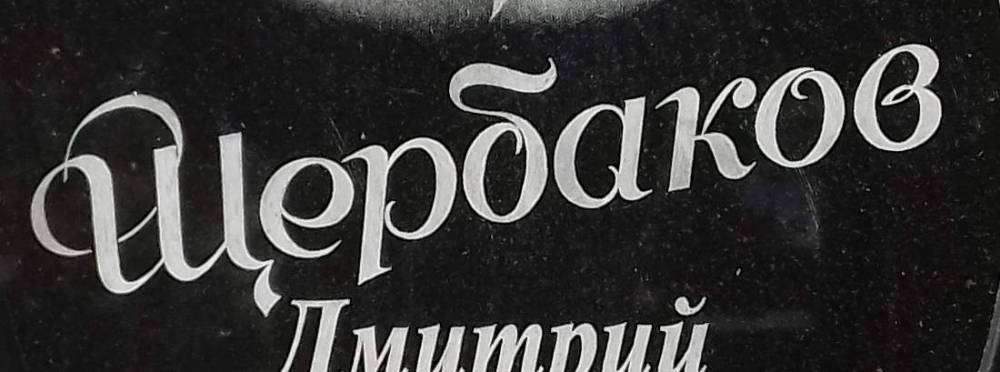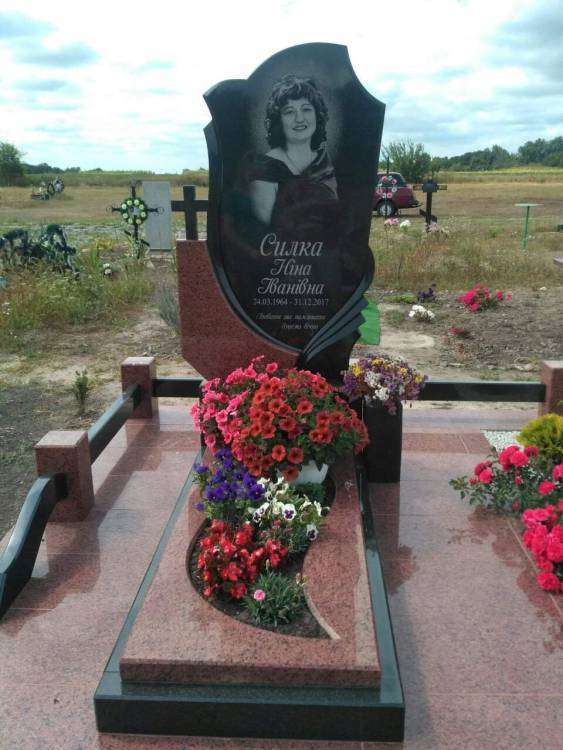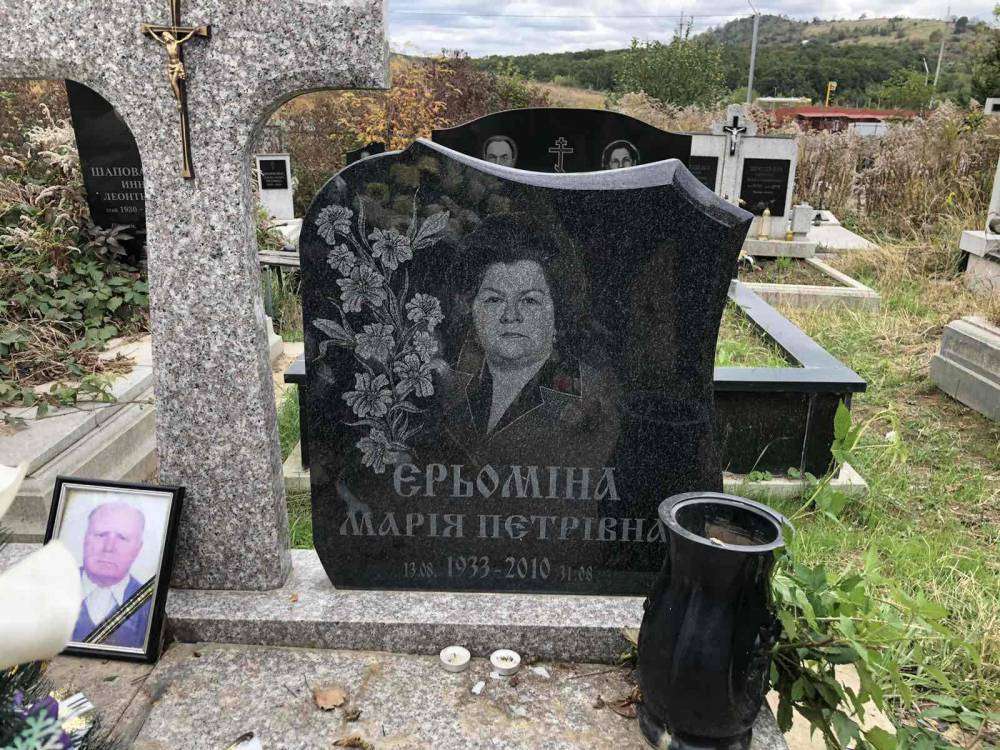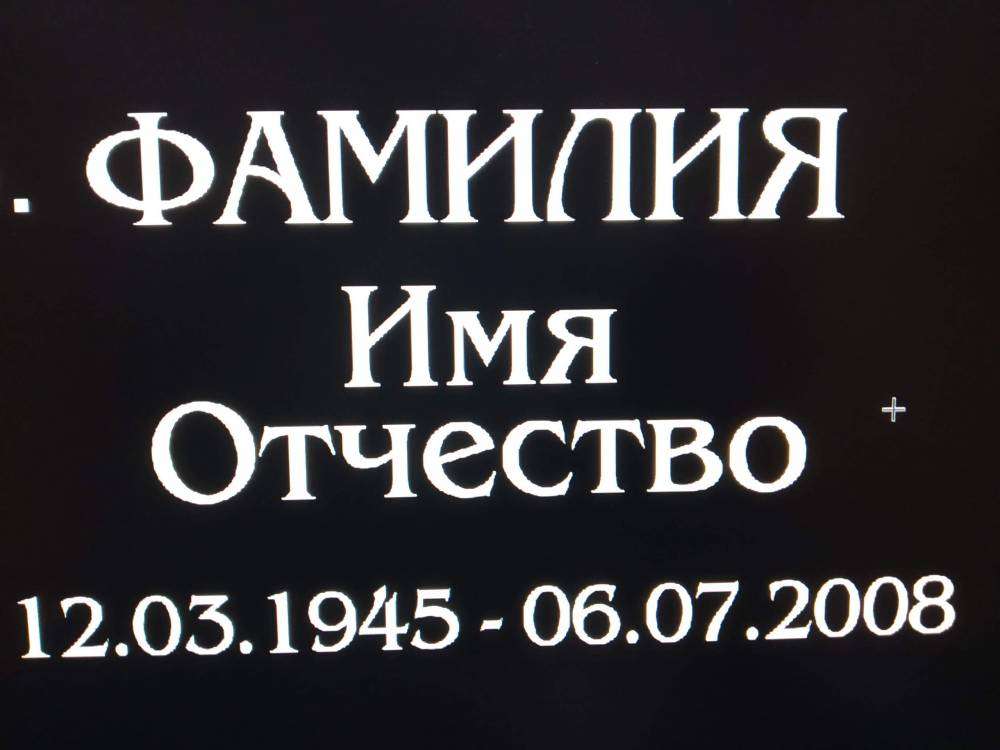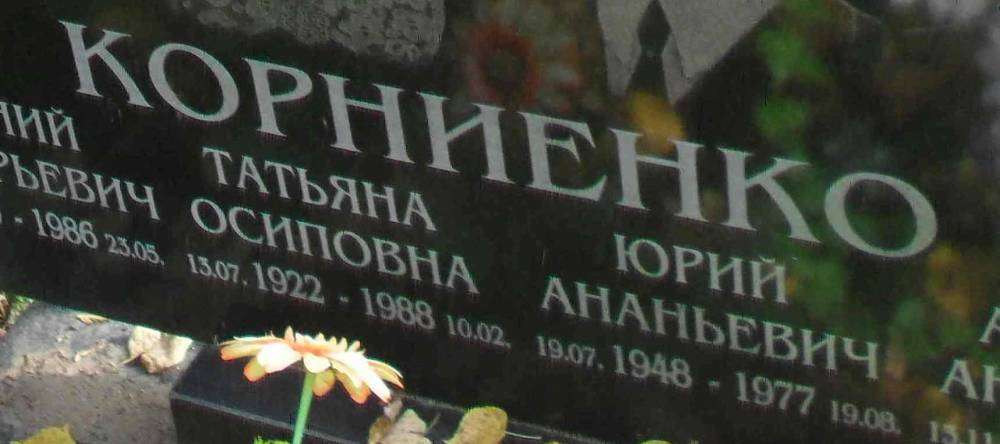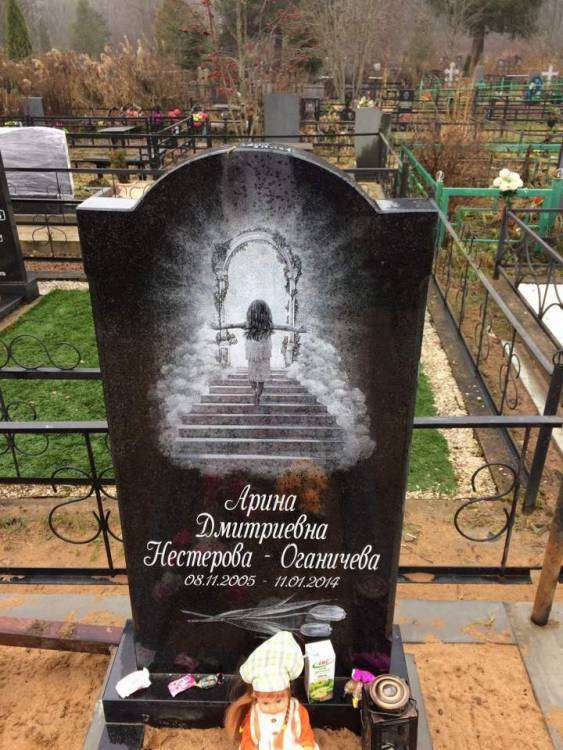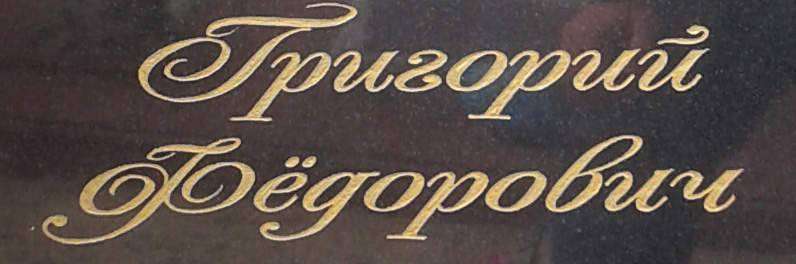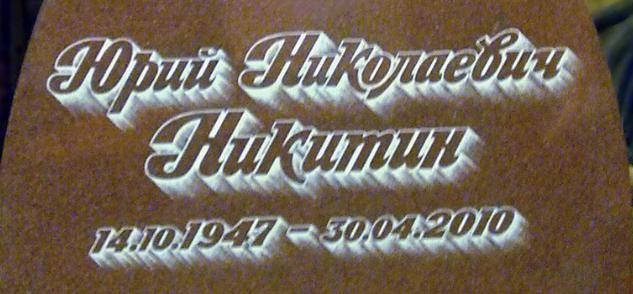
Макс.Макс Опубликовано 4 октября, 2019 Здравтвуйте нужен такой шрифт как он называеться.Помогите найти.
zlojsultan Опубликовано 16 октября, 2019 Здравствуйте, помогите пожалуйста найти такой шрифт
Mystery Опубликовано 31 октября, 2019 Вот таким озадачили.... Кто, что скажет? Что за шрифт?
hrystik89 Опубликовано 28 ноября, 2019 Здравствуйте. Помогите найти шрифт. Заранее спасибо.
Вячеслав00 Опубликовано 3 декабря, 2019 Приветствую, помогите найти шрифт http://prntscr.com/q5tkxk
Смешарик Опубликовано 4 декабря, 2019 Помогите пожалуйста со шрифтом. В инете поискала-не нашла. Есть очень похожие, но заглавные буквы другие. А все дело в них.... 17 минут назад, Смешарик сказал: Помогите пожалуйста со шрифтом. В инете поискала-не нашла. Есть очень похожие, но заглавные буквы другие. А все дело в них.... три дня по инету искала!!!а он на предыдущей странице!!!! сообщение хотела удалить-не нашла где) а посему сорри за беспокойство)) всем удачного дня) (сама спросила.....сама ответила....)
zelenok Опубликовано 4 декабря, 2019 Подскажите неграмотному, что за шрифт? Как-то он у нас совсем не распространён.
marinn Опубликовано 4 декабря, 2019 @zelenok На AGBengaly похож, только заглавные. 1
Yuriu Опубликовано 4 декабря, 2019 @zelenok https://www.fonts-online.ru/font/AGBenguiat-Cyr-Book 1
slovorub70 Опубликовано 4 декабря, 2019 21 час назад, Вячеслав00 сказал: Приветствую, помогите найти шрифт http://prntscr.com/q5tkxk Это ручная работа и шрифт авторский. Делал мой коллега.
nod62 Опубликовано 10 декабря, 2019 Чет не могу вспомнить что за шрифт использовал... подскажите пожалуйста.